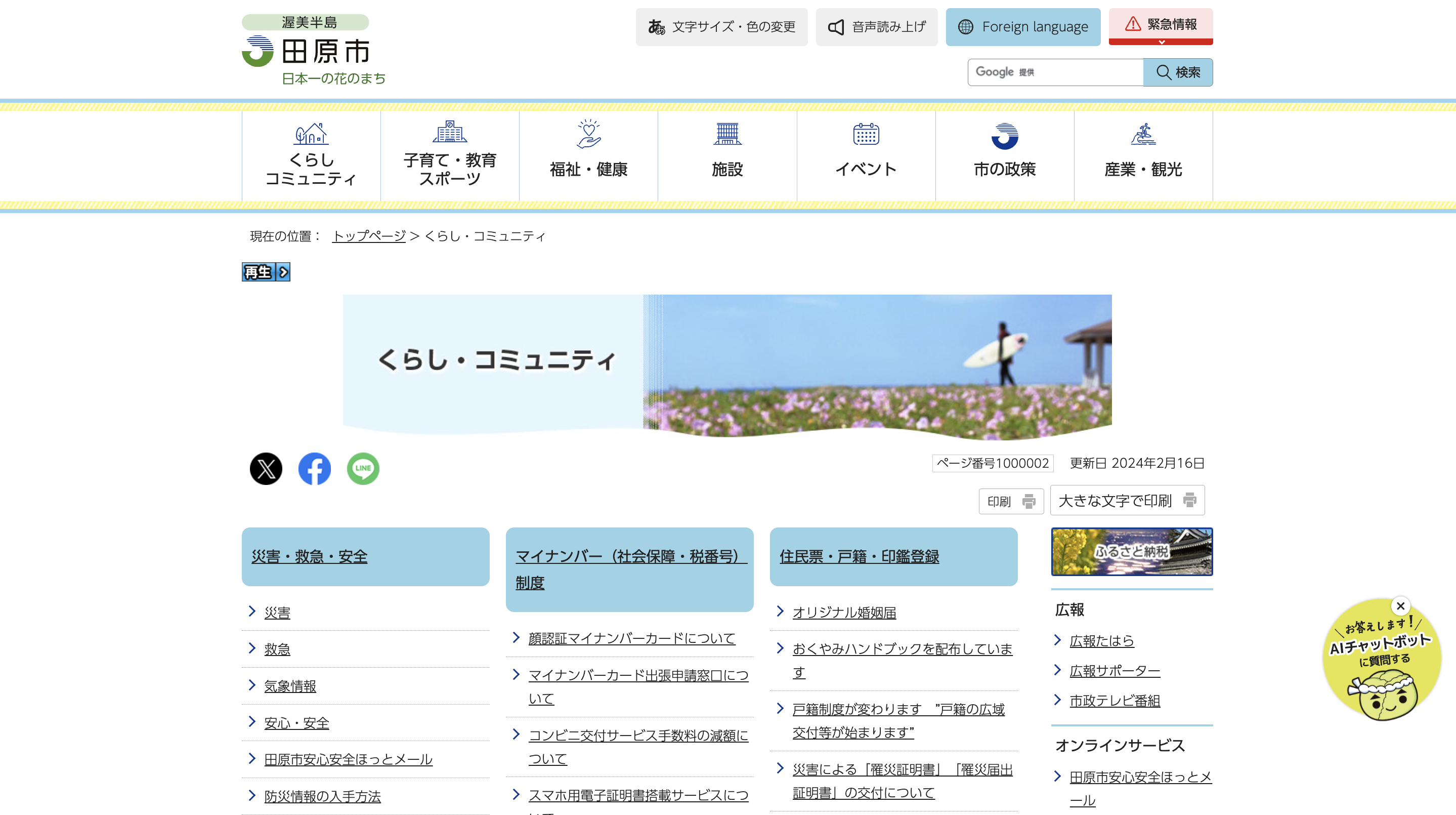
モリサワのWebフォントサービス「TypeSquare」と「UD新ゴ」が愛知県田原市ホームページに採用
株式会社モリサワのWebフォントサービス「TypeSquare」およびユニバーサルデザイン(UD)フォントである「UD新ゴ」が愛知県田原市ホームページに採用されました。
田原市ホームページは2024年2月のリニューアルに伴い、掲載する情報を整理し、障害者や高齢者、日本語を母語としない人などにも配慮して、誰もが分かりやすく必要な情報に辿り着けるように、デザインが刷新されました。
採用された「UD新ゴ」は、ロービジョンやデジタルデバイスにおける可視性・可読性の比較研究により、読みやすさ、判別のしやすさに関するエビデンスを取得しているUDフォントです。濁点、半濁点を大きくして区別をつけやすくしているほか、シルエットの似た文字を判別しやすくするため、個々の文字の形が明瞭なデザインとなっています。
また、リニューアルに際し導入されたWebフォントサービス「TypeSquare」は、指定したフォントを閲覧者側のWebブラウザに表示させることができるため、閲覧者のデバイス環境に関わらず、UDに配慮したWebデザインが実現します。
モリサワのUDフォントについて
「文字のかたちがわかりやすいこと」「文章が読みやすいこと」「読み間違えにくいこと」をコンセプトに開発されています。具体的には、濁点、半濁点を大きくして、区別をつけやすくしているほか、シルエットの似た文字を判別しやすくするために、はなれを明確にするなどの工夫がされています。また、第三者機関と共同で可視性・可読性に関する比較研究報告を実施しています。
「TypeSquare」について
インターネットを介してフォントを配信し、Webブラウザで表示させる「Webフォント」のサービスです。Webサイトの検索性の向上が見込まれるだけでなく、自動翻訳や音声読み上げといった機能とも連携しやすくなり、伝えたい情報を的確に届けられるようになります。一般的な明朝体やゴシック体はもちろん、デザイン書体やUD書体、多言語書体などモリサワの豊富な書体ラインナップで、Webサイトの多彩なデザインを実現します。